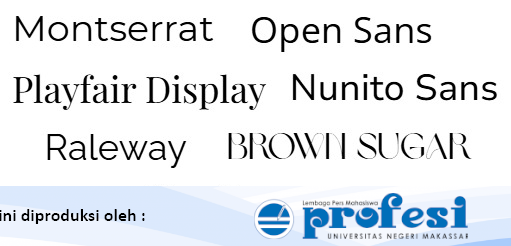
7 Rekomendasi Font Canva Terbaik untuk Desain Menarik dan Profesional yang Wajib Dicoba
Font adalah elemen krusial dalam dunia desain digital yang dapat menentukan kesan visual dan profesionalitas sebuah karya. Bagi pengguna Canva, memilih jenis font yang tepat dapat membantu memperkuat pesan dan membuat tampilan desain lebih menarik serta estetik. Canva menyediakan beragam pilihan font baik gratis maupun premium yang memudahkan desainer, mulai dari pemula hingga profesional.
Berikut tujuh rekomendasi font terbaik di Canva yang tidak hanya populer tapi juga sesuai untuk berbagai kebutuhan desain. Font ini dapat diaplikasikan untuk media sosial, presentasi, branding, hingga proyek kreatif lainnya dengan hasil yang lebih profesional dan estetik.
1. Montserrat
Montserrat adalah font sans serif yang sangat populer karena tampilannya yang modern dan bersih. Font ini ideal digunakan untuk judul, logo, atau teks utama pada desain yang ingin menonjolkan kesan minimalis dan profesional. Menurut para desainer, Montserrat mudah dibaca dan memberikan kesan kuat dan elegan.
2. Playfair Display
Font serif ini cocok untuk desain yang menginginkan nuansa elegan dan berkelas. Playfair Display sering ditemukan pada desain majalah, undangan, serta branding produk yang ingin tampil klasik dan mewah. Karakter font ini memberikan kesan formal namun tetap artistik sehingga cocok untuk keperluan branding dengan sentuhan high-end.
3. Raleway
Dikenal dengan bentuk huruf yang ramping dan modern, Raleway sangat cocok untuk tampilan yang bersih dan profesional, seperti presentasi bisnis atau portofolio digital. Kombinasi font ini dengan font serif bisa menciptakan keseimbangan visual yang menarik dan tidak membosankan. Desain menjadi lebih segar sekaligus mudah dibaca.
4. Brown Sugar
Brown Sugar adalah font dekoratif dengan karakter lembut namun jelas terbaca. Font ini sangat cocok untuk desain yang menonjolkan kreativitas dan estetika, seperti konten media sosial, poster, atau kemasan produk. Karakter font ini memberikan sentuhan unik dan menarik perhatian tanpa mengorbankan keterbacaan.
5. Open Sans
Open Sans merupakan salah satu font paling fleksibel yang ada di Canva. Bentuk hurufnya sederhana dan jelas menjadikannya pilihan utama untuk teks panjang, baik di platform digital maupun cetak. Desainer sering memadukan Open Sans dengan font tebal seperti Montserrat untuk menciptakan efek kontras yang menarik secara visual.
6. The Seasons
Font serif bergaya klasik ini memberikan kesan dramatis dan artistik. The Seasons sangat ideal untuk desain undangan, brosur, atau proyek kreatif yang membutuhkan sentuhan elegan dan berkarakter. Huruf yang tinggi dan bergaya membuat teks terlihat menonjol serta memberikan kesan unik pada desain.
7. Nunito Sans
Nunito Sans menawarkan kesan ramah serta modern dengan bentuk huruf yang membulat dan mudah dibaca. Font ini sering digunakan pada website, aplikasi, dan materi promosi yang menginginkan tampilan profesional tanpa terasa kaku. Penggunaan Nunito Sans dapat membuat komunikasi visual menjadi lebih bersahabat bagi audiens.
Memilih font yang sesuai bukan hanya soal estetika, tetapi juga soal bagaimana font tersebut dapat memperkuat pesan dan karakter desain. Canva, dengan koleksi font yang luas dan mudah digunakan, memberikan kemudahan bagi desainer dalam menemukan font yang tepat untuk berbagai kebutuhan. Dengan memanfaatkan font-font ini, kamu dapat membuat karya desain yang tidak hanya menarik tapi juga profesional dan sesuai dengan tujuan komunikasimu.